השאלון עם רם סלים
הכירו את רם סלים, מעצב ואמן, בוגר טרי של המחלקה לתקשורת חזותית בשנקר. רם נולד בשנת 1997, במקור מנתניה, והיום מתגורר בתל־אביב. הרקע המרכזי שלו הוא ברישום, והוא למד במסלול איור, אך החיים, כמו החיים, הובילו אותו להתמקד בעיקר בטיפוגרפיה במהלך התואר. באופן כללי, רם הוא יוצר רב־תחומי שנהנה מכל מדיום יצירתי, כל עוד הוא מצליח להכניס בו משהו מהנשמה שלו. רם אוהב מאד אומנות, תרבות, מיתולוגיה והיסטוריה מהמזרח הקדום, ותמיד מנסה להכניס רמיזות מעולמות אלה בעבודותיו כשמתאפשר לו.
על איזה פרויקט מעניין עבדת לאחרונה?
אני בוגר טרי של שנקר, אז הפרויקט הכי מעניין ורלוונטי שיצא לי לעבוד עליו לאחרונה הוא כמובן פרויקט הגמר שלי. זה פרויקט שמביא לדעתי לידי ביטוי את כל מה שעניין אותי בתואר והרבה ממה שמעניין אותי כמעצב וכאדם. מכיוון שלמדתי במסלול איור לא יצא לי לעצב יותר מדי ספרים במהלך התואר, והיה לי חשוב מאוד שזה יקרה. תוך כדי העבודה על הפרויקט הרבה בו השתנה, אבל הדבר שהיה הכי חשוב לי הוא ההגשמה הזו של החלום לעצב ספר שכולו חגיגה של עיצוב, וכך היה.
פרויקט הגמר של רם, ״שלושה כתבים״, הוא פרויקט בטיפוגרפיה ניסיונית שבו יצר שלוש מערכות כתב אלטרנטיביות לעברית. כל מערכת נובעת מתפיסה שונה של המילה – מילה ככוח מאגי, מילה כרעיון קדמוני ומילה כצופן, וכל אחת מהן מתורגמת לשיטה ייחודית לעיצוב האות. כך, מערכת אחת מבוססת על ערכים גימטריים, השנייה בהשראת כתב קדם־כנעני, והשלישית נשענת על ערכי unicode. הפרויקט מתפתח כציר כרונולוגי: הוא נפתח בשלב המחקר, המתועד בספר ההסברים; ממשיך לשלב הפיתוח האסתטי, שבו חוברת הספסימנים מציגה גופנים לכל מערכת; ומגיע לשלב היישום, שבו ספר העיצובים מציג את האותיות בפעולה במגוון הקשרים.
מה גורם לך להתרגש ולרצות לעצב וליצור?
הרצון ליצור הוא משהו מובנה בתוכי, אני מצייר, רושם ויוצר ממש מהרגע שבו אני זוכר את עצמי, אני לא זוכר מציאות שבה לא הייתי אדם יוצר. אז במקרה שלי זה באמת הטבע שלי, זה יוצא מתוכי. אם אצטרך לנקוב במשהו ספציפי – אני פריק של תרבות המזרח התיכון הקדום, ומושפע ממנו הרבה מבחינה ויזואלית וקונספטואלית. אומנות ואדריכלות, מיתולוגיה ודת, מבני ישראל הקדומים ועד לפרסים ולאשורים.
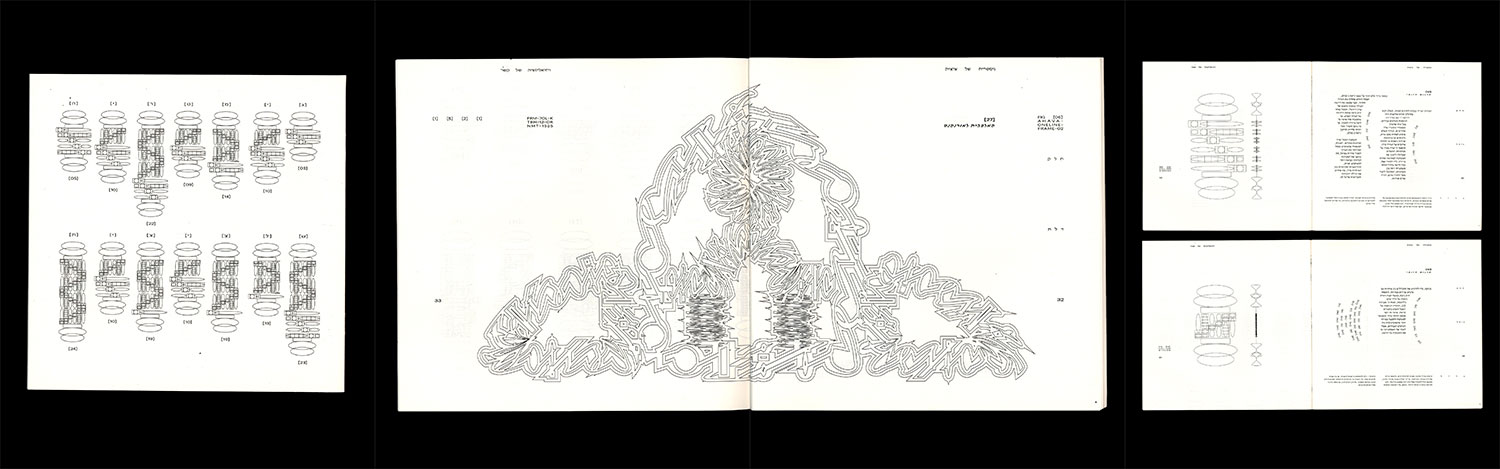
גימטריה של ציצית – פרויקט של רם בטיפוגרפיה ניסיונית. העבודה נולדה מתוך מחקר על קשירת ציציות, שבו רם גילה כי רבים נוהגים לטמון בפתילות ערכים גימטריים של שם השם (10, 5, 6, 5), כאשר מספר הליפופים נעשה כנגד הערך של האות. מתוך התובנה הזו יצר אלפבית גרפי־גימטרי המבוסס על הרעיון של קשירות ולולאות. התוצרים והמחקר נאספו לחוברת עם הסברים ויישומים.
במה היית עוסק אם לא היית מעצב?
זו קצת רמאות אבל אם לא הייתי מעצב גרפי הייתי מעצב אופנה. או מעצב משחקים. או פסל. או שחקן.
איפה אתה רואה את עצמך בעוד חמש שנים מהיום?
בעזרת השם משגשג בתחומי. לא רוצה להגדיר גבולות גזרה ספציפיים כי אני אוהב לתת לחיים לזרום ולהביא אותי למקומות לא צפויים, אבל הכי חשוב שאני והסובבים אותי נהיה הכי מאושרים שיש, ושיהיה לי מעניין ויפרה את הרצון שלי ליצור ולעשות עוד ועוד.
ספר פרוזה/עיון אחרון שקראת.
עבר זמן מאז שקראתי אותו אבל ״ראשית ישראל״ של ישראל פינקלשטיין, ספר שמנסה להתחקות אחרי המקורות הארכאיים של עם ישראל על פי הממצא הארכיאולוגי. יש לי גם קצת חילוקי דעות עם המחקר, אבל מעניין ושווה קריאה לגמרי.
באיזה פונט אתה רוצה שיכתבו על המצבה שלך?